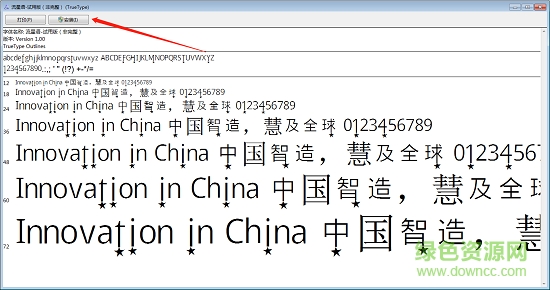
義啟流星語字體官方免費(fèi)版是一款非常簡單的簡筆字體,字體中添加了部分流星作為主要的特色,簡答而又增添了部分裝飾,簡約而又不失美感,喜歡的用戶快來綠色資源網(wǎng)下載吧!
義啟流星語字體是一款由義啟字體官網(wǎng)提供的中文簡體藝術(shù)字體,字體采用簡約的風(fēng)格設(shè)計,將流星的特色融入到字體中,讓你用戶能夠感受到一款非常豐富的字體!
擁有大小不一的字體外形,并在許多字體筆畫下方加入流星圖案,
流星位置恰到好處,完全不會影響字體識別度,能夠支持日常輸出的多種格式,
適合應(yīng)用于廣告設(shè)計、平面、雜志、海報等字體使用!